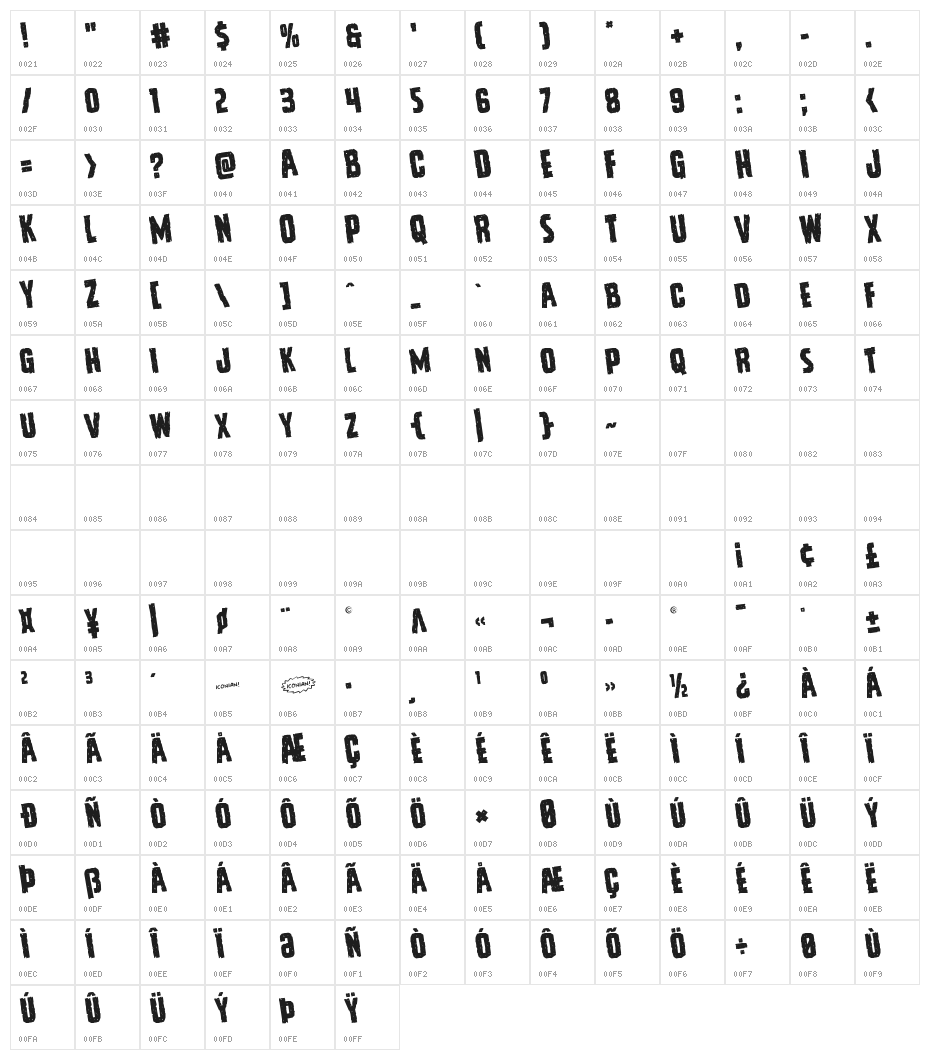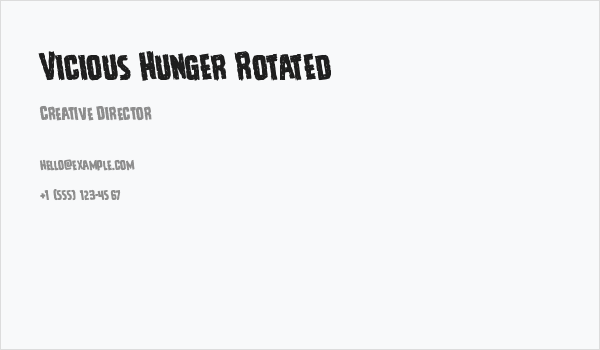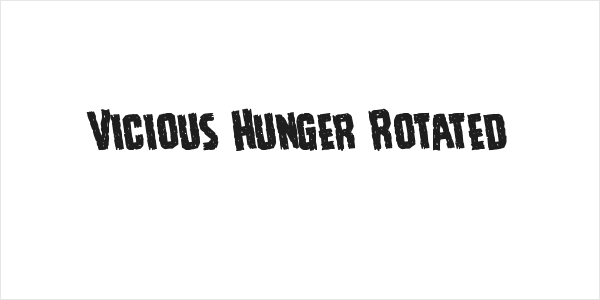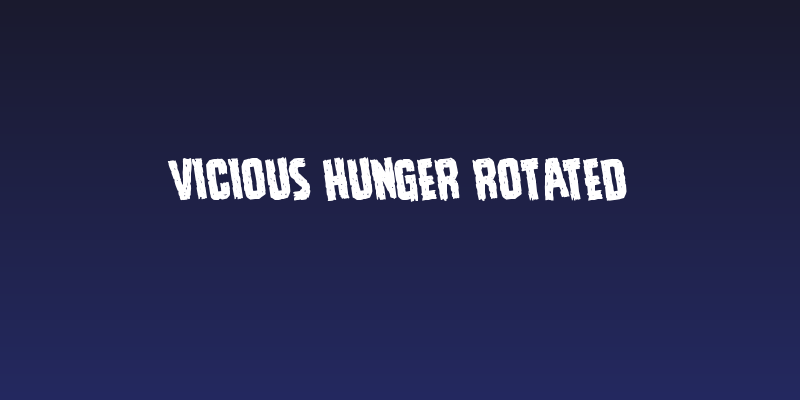
Vicious Hunger Rotated Font
| الفئات | Graffiti |
| النمط العام | Urban, Edgy, Distressed |
| مشاريع مقترحة | Ideal for album covers, streetwear branding, posters, and event flyers. |